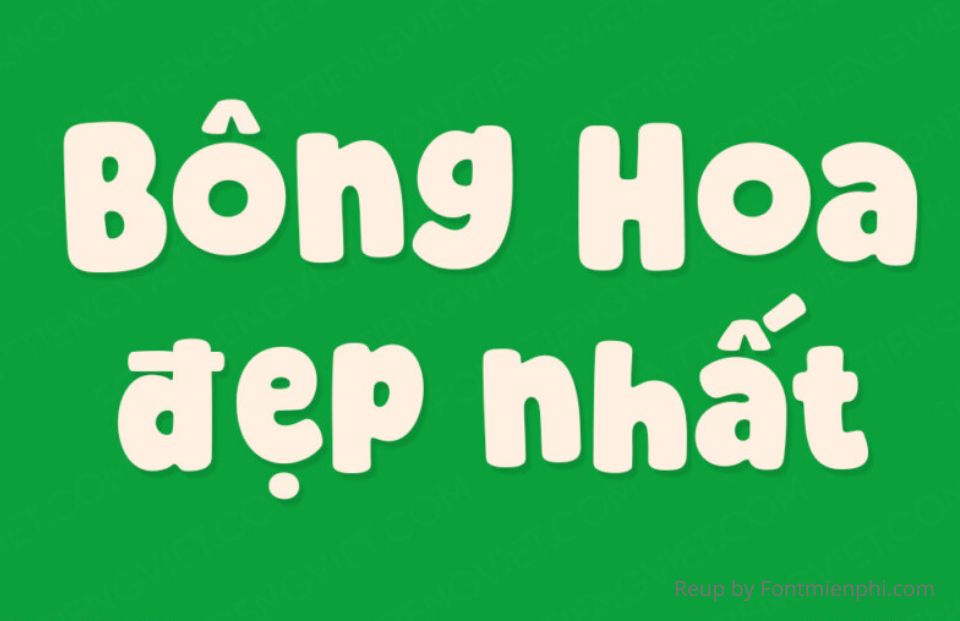
Font Việt hóa 1FTV VIP Super Bouncer – Nét chữ hoạt hình vui nhộn, nổi bật
1FTV VIP Super Bouncer là font chữ Việt hóa mang phong cách hoạt hình vui nhộn, nổi bật với những đường nét dày dặn, mềm mại và giàu năng lượng. Kiểu chữ này đặc biệt phù hợp với các thiết kế dành cho trẻ em, poster giải trí, tiêu đề video, hình ảnh quảng cáo, bao bì sản phẩm và nội dung mạng xã hội.
Với khả năng hiển thị tiếng Việt đầy đủ, Font Việt hóa 1FTV VIP Super Bouncer giúp người dùng dễ dàng sáng tạo những dòng tiêu đề bắt mắt mà không gặp lỗi dấu hay lỗi ký tự tiếng Việt.
• Phong cách: Cartoon, Display, Fancy, Kids
Đặc điểm nổi bật của font Super Bouncer Việt hóa
Phong cách hoạt hình vui nhộn Font Việt hóa 1FTV VIP Super Bouncer
Điểm thu hút đầu tiên của 1FTV VIP Super Bouncer là kiểu dáng chữ sinh động và có phần tinh nghịch. Các ký tự được thiết kế theo phong cách trang trí, tạo cảm giác như đang chuyển động hoặc bật nảy trên bề mặt thiết kế.
Nhờ đặc điểm này, font có thể nhanh chóng thu hút ánh nhìn khi được sử dụng cho tiêu đề, slogan hoặc những nội dung cần tạo điểm nhấn.
Nét chữ dày, dễ tạo hiệu ứng
Super Bouncer sở hữu phần thân chữ tương đối đậm, giúp nội dung duy trì khả năng nhận diện tốt trên nhiều loại nền khác nhau. Người thiết kế có thể dễ dàng kết hợp font với các hiệu ứng như:
• Viền chữ nhiều lớp
• Đổ bóng 3D
• Hiệu ứng nổi
• Chuyển màu gradient
• Texture giấy, nhựa hoặc kẹo ngọt
• Hiệu ứng sticker
• Viền trắng dành cho thumbnail
Khi được phối màu phù hợp, font có thể tạo nên những tiêu đề trẻ trung, đáng yêu và mang tính giải trí cao.
Hỗ trợ gõ tiếng Việt
Phiên bản 1FTV VIP Super Bouncer Việt hóa đã được bổ sung và xử lý hệ thống ký tự tiếng Việt. Người dùng có thể nhập nội dung có dấu trực tiếp mà không cần chỉnh sửa từng ký tự thủ công.
Font hỗ trợ các chữ cái và dấu tiếng Việt thường dùng như:
Ă, Â, Đ, Ê, Ô, Ơ, Ư cùng hệ thống dấu sắc, huyền, hỏi, ngã và nặng.
Khả năng hỗ trợ tiếng Việt giúp font phù hợp với các dự án thiết kế dành cho thị trường Việt Nam như banner, hình ảnh Facebook, thumbnail YouTube, bảng hiệu, bao bì và nội dung quảng cáo.
Font Việt hóa 1FTV VIP Super Bouncer phù hợp với thiết kế nào?
Thiết kế dành cho trẻ em
Phong cách chữ mềm mại và vui nhộn giúp Super Bouncer trở thành lựa chọn phù hợp cho:
• Poster trường mầm non
• Bảng chữ cái cho trẻ
• Truyện tranh thiếu nhi
• Thiệp sinh nhật
• Đồ chơi trẻ em
• Sách tô màu
• Banner sự kiện gia đình
• Chương trình vui chơi dành cho bé
Font Việt hóa 1FTV VIP Super Bouncer Thumbnail YouTube và video giải trí
Nét chữ dày giúp tiêu đề vẫn dễ đọc khi hình ảnh được thu nhỏ. Người dùng có thể sử dụng font cho thumbnail video về:
• Hoạt hình
• Đồ chơi
• Trò chơi
• Ẩm thực
• Thử thách vui nhộn
• Vlog gia đình
• Nội dung dành cho trẻ nhỏ
Để tiêu đề nổi bật hơn, bạn có thể thêm viền trắng hoặc viền màu tương phản, sau đó kết hợp với hiệu ứng đổ bóng nhẹ.
Bao bì sản phẩm
1FTV VIP Super Bouncer cũng có thể được ứng dụng trong thiết kế bao bì cho các sản phẩm mang phong cách trẻ trung như:
• Bánh kẹo
• Kem
• Đồ uống
• Đồ chơi
• Sản phẩm cho trẻ em
• Quà tặng
• Phụ kiện handmade
• Sản phẩm trang trí
Kiểu chữ vui vẻ giúp bao bì trở nên thân thiện, dễ nhận biết và tạo cảm giác gần gũi với người mua.
Poster, banner và bài đăng mạng xã hội
Font phù hợp với những nội dung cần thể hiện không khí sôi động như chương trình khuyến mãi, minigame, khai trương, sinh nhật, lễ hội hoặc sự kiện giải trí.
Một số nội dung gợi ý:
• Siêu ưu đãi
• Khuyến mãi cực vui
• Quà tặng bất ngờ
• Chào hè rực rỡ
• Sinh nhật đáng yêu
• Ngày hội gia đình
• Bé vui đến trường
• Món ngon mỗi ngày
Cách phối màu với Font Việt hóa 1FTV VIP Super Bouncer
Do mang phong cách hoạt hình, font sẽ phát huy hiệu quả tốt khi được kết hợp với những bảng màu tươi sáng.
Phong cách kẹo ngọt
Sử dụng các màu hồng, tím pastel, xanh da trời, vàng kem và trắng. Cách phối màu này phù hợp với thiết kế sinh nhật, bánh kẹo, đồ chơi hoặc sản phẩm dành cho trẻ em.
Phong cách năng động
Kết hợp màu đỏ, vàng, xanh dương và cam. Đây là bảng màu phù hợp với thumbnail video, poster trò chơi và chương trình khuyến mãi.